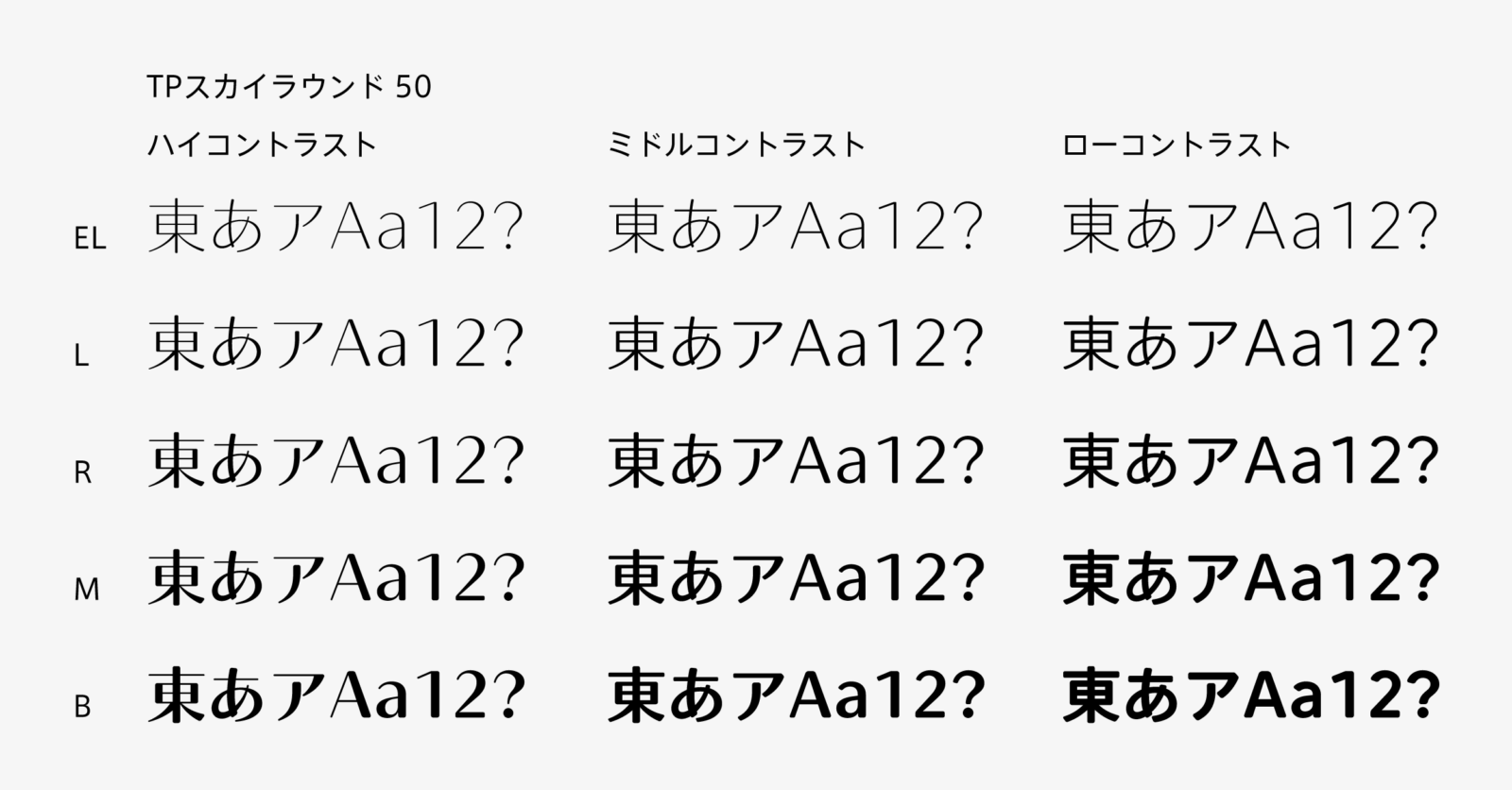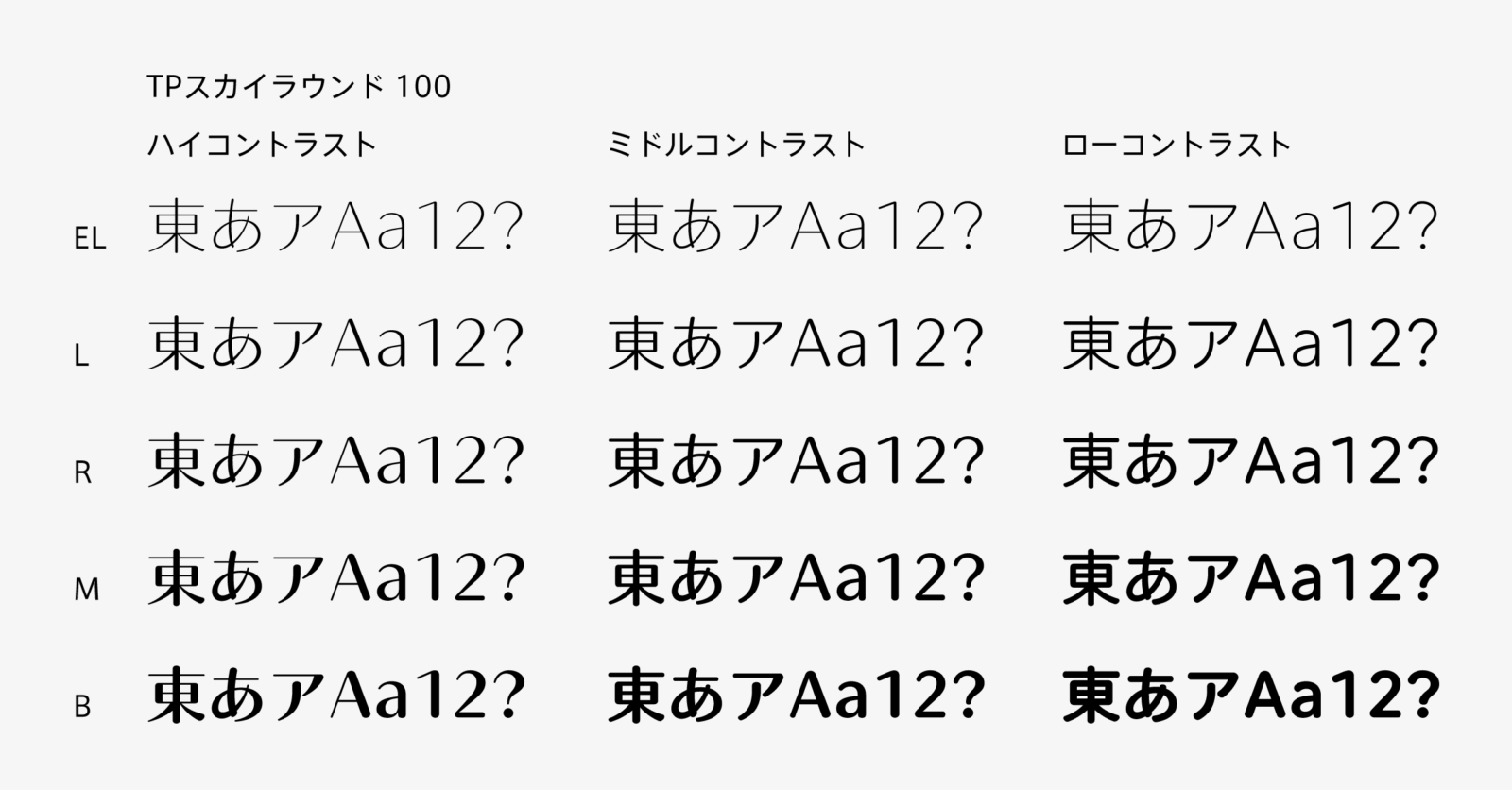
タイププロジェクト、TPスカイファミリーのラウンドフォントを発表
TPスカイラウンド 50 とTPスカイラウンド 100 の全30フォントをTPコネクトで提供
タイププロジェクト株式会社 (東京都練馬区 代表取締役社長 鈴木 功、以下 タイププロジェクト) は、抑揚サンセリフ体であるTPスカイファミリーの新フォントとして、「TPスカイラウンド 50」および「TPスカイラウンド 100」を発表しました。TPスカイラウンドシリーズは、タイププロジェクトが提供するフォントを年間定額でご利用いただけるサービス「TPコネクト」で提供いたします。
スクリーン表示に適した本格的なフォントで、ウエイト・コントラスト・字幅の3つの軸を持つ初めての日本語フォントであるTPスカイに、角アールの度合いを選べるラウンドが加わりました。TPスカイラウンド50とTPスカイラウンド100は、それぞれ3つのコントラスト(ハイ/ミドル/ロー) と5つのウエイト(EL/L/R/M/B) で構成され、合わせて30フォントのラウンドファミリーとなります。
タイププロジェクトの代表取締役 鈴木 功は、「視認性が高いTPスカイの書体設計をベースに、ストロークの先端を丸めることで親しみやすさと使いやすさが格段に向上したと自負しています。横組み用途で開発したAXIS Fontに対して、TPスカイシリーズは、縦組みでの安定度も十分に考慮しました。TPスカイのラウンドシリーズは、抑揚サンセリフのカテゴリーにおける新たな定番を目指し、幅広い分野、さまざまな場面での使用に耐えうるファミリーですので、目的や用途に応じて最適なフォントをお選びいただけます」と述べています。
シャープさが持ち味のTPスカイをわずかにマイルドにしたTPスカイラウンド50は、異なるウエイトでも同じアールに見えるよう、ウエイトによって角アールの半径を変え、視覚的なバランス調整と印象の統一をはかりました。また、丸ゴシックでありながらもすっきりと甘さを抑えたTPスカイラウンド100は、先端部を正円であらわしたAXISラウンドとは異なり、85%の扁平な円を採用しています。
- 全45フォント
3コントラスト :ハイ、ミドル、ロー